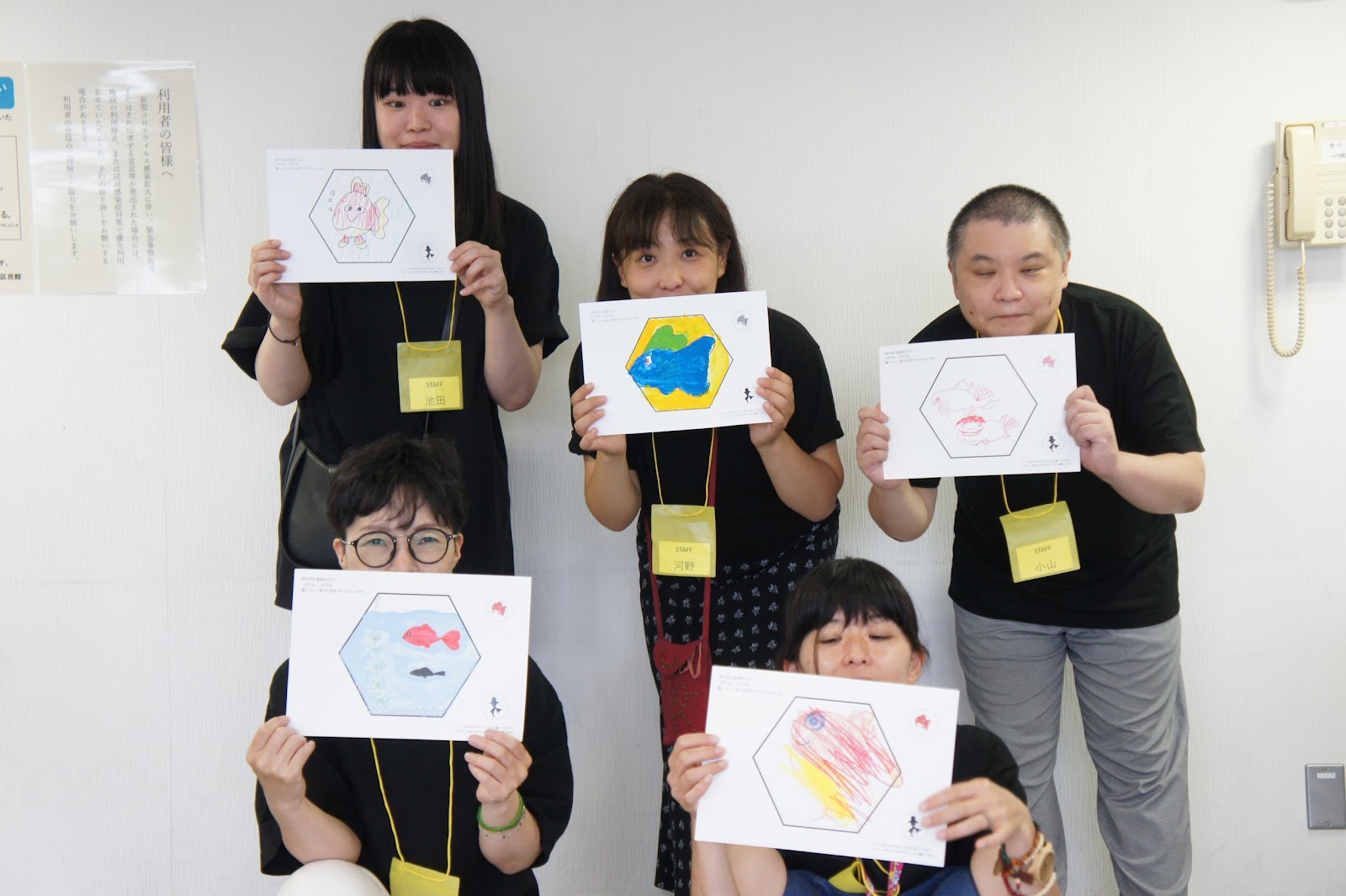
江戸川区独自の草の根ネットワークで 地域共生社会づくりに一石を投じたい
障がいのある人を社会的弱者ではなく、 かっこいいアーティストに
江戸川区内の障がいのある人たちのアート活動を支援し、社会参加と地域共生社会の実現を目指して設立されたのが“エドてらす”です。東京2020大会の開催に合わせて江戸川区では応援グッズを作ろうという動きがあり、準備を進めていたところ、コロナ禍による延期などが原因で計画は頓挫。そこに飛び込んできたのがご当地フォントの取り組みでした。
江戸川区に関係の深い“金魚”をモチーフに、作品作りに取り組むみなさん。“金魚だから赤”じゃなくてもいい。色も形も自由に
「エドてらすは、区内の事業所だけではなく、個人、障がいのあるお子さんを持つご家族、みんなを集めて仲間になり“地域を作る”ことを目的とした有志の団体です。ご当地フォントは、その理念とぴったりマッチしていると思い、参画を決めました。ただ作品を展示するといったこととは違う形で社会参加できることが魅力でした」
障がいのある方の言動はときに問題行動とされ、迷惑や面倒だと思われがち。しかし、アートを切り口にすれば“面白い”という高評価につながります。かつて、昔の作業所で売られていた商品のマーケティングのように、彼らを障がいのある人という社会的弱者のラベリングに留めるか、“かっこいいアーティスト”にするかは、自分たちソーシャルワーカーのマネージメント次第だという自負が、エドてらすの方々にはありました。
「こういうことをやりますという告知を始めたのと、コロナの感染拡大と学校の夏休みがちょうど重なってしまいました。応募可能な方を、江戸川区全体の障がいを持つ方々と大きく広げたので、自分たちが出向いて説明するほか、描き方を説明したYouTube動画を作ったり、描く紙は事務局で準備した方がいいと急遽印刷会社に注文したり、とにかくバタバタでしたね」
活動の外への広がりの中で、意外な一面を見せてくれた方も
江戸川区のご当地フォント“エドフォント”のモチーフになったのは、明治時代に地元で養殖が始まった金魚、区の花である桜、そして後ろではなく前に進む性質のあるトンボ。みなさんはこれらのモチーフにどのように取り組んでいったのでしょうか。
「事業所のアートプログラムで見せる、気心の知れた仲間同士のおしゃべりでは、下品な失言ばかりしていたプレイボーイ風な方が、ご当地フォントに取り組んでいるときは、紳士的に場を和ませたり、デザイナーさんに自分の作りたいイメージを相談したり、すごく真剣になっていました。活動が外に広がり外と繋がったからこそ、こういう一面があると気づかされたのは良かったなと思います」
作品作りのため、ワークショップを開催
結果集まったフォントや絵は何と650点。事業所をあげて、“来所者全員で描こう!”というかけ声のもと、しばらくペンを持っていなかった方が久しぶりに取り組んでくれたこともあったのだとか。スタッフも楽しいひとときだったそうです。
「〆切ギリギリに学校が夏休みなのでと、事業所までわざわざお母様と共に届けてくれた男子中学生がいました。せっかくなので施設をご案内したら興味を持っていただいたようです。他にも“親の目には蚊にしか見えない”と言っていたお子さんのトンボの作品が選ばれて、大喜びの親御さんがいたり、ずっと引きこもりで家を出られなかった方が、郵送ではなくどうしても自分の手で持ってきたいと訪れてくれたのには、本当に驚かされました」
自分が手がけた作品が広く知られ、障がいのある人に対する啓発を担えることは、作者本人の自尊心の底上げはもちろん、携わるスタッフのやりがいも繋がっているようです。集まった650点の作品のお披露目会も計画中とのことで、今後の広がりに期待が高まります。